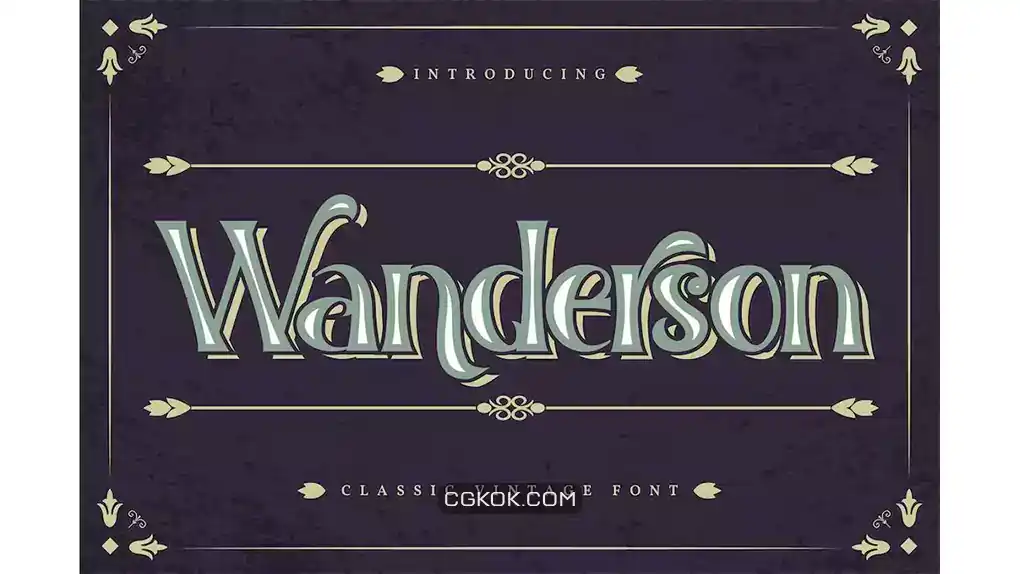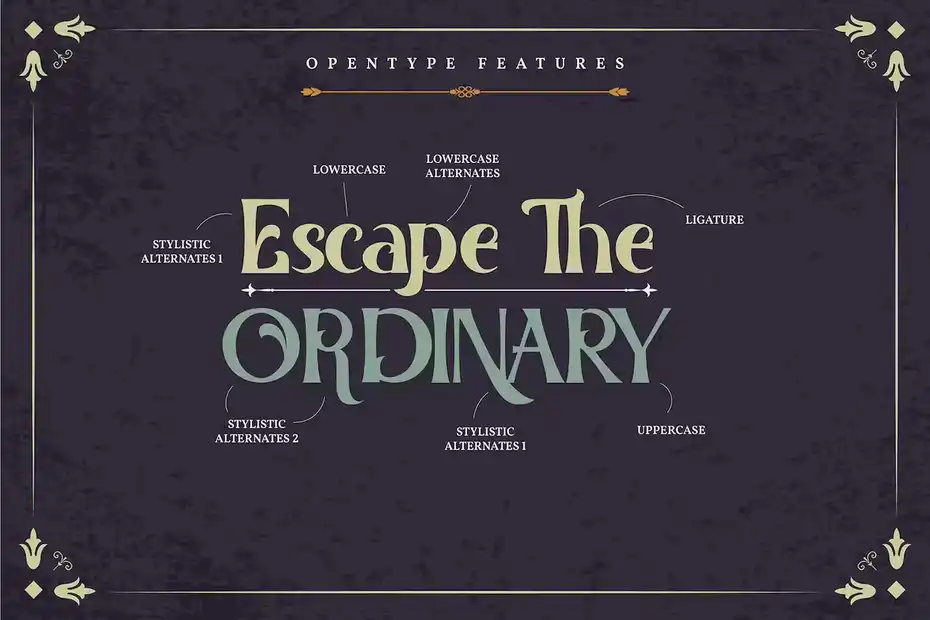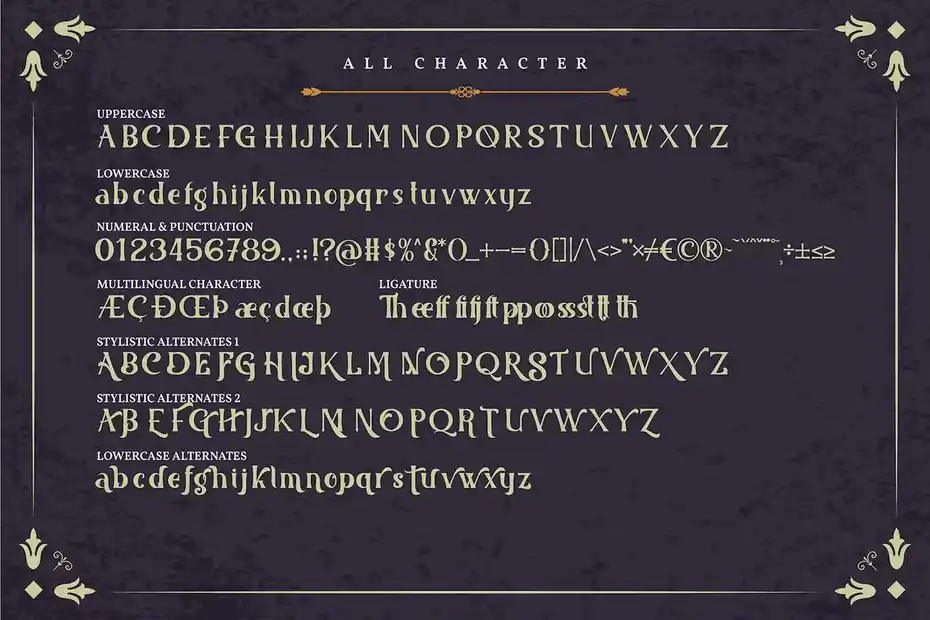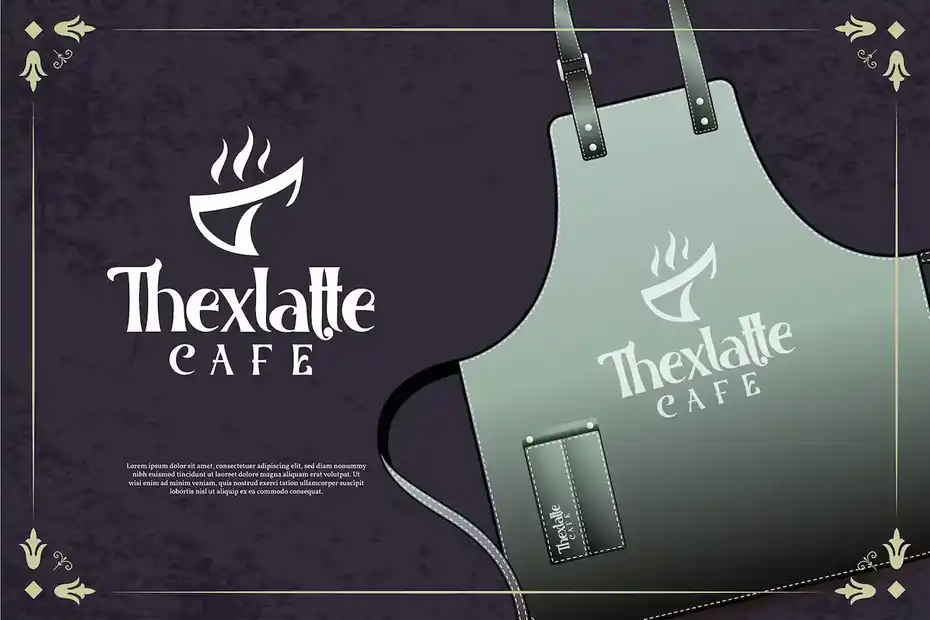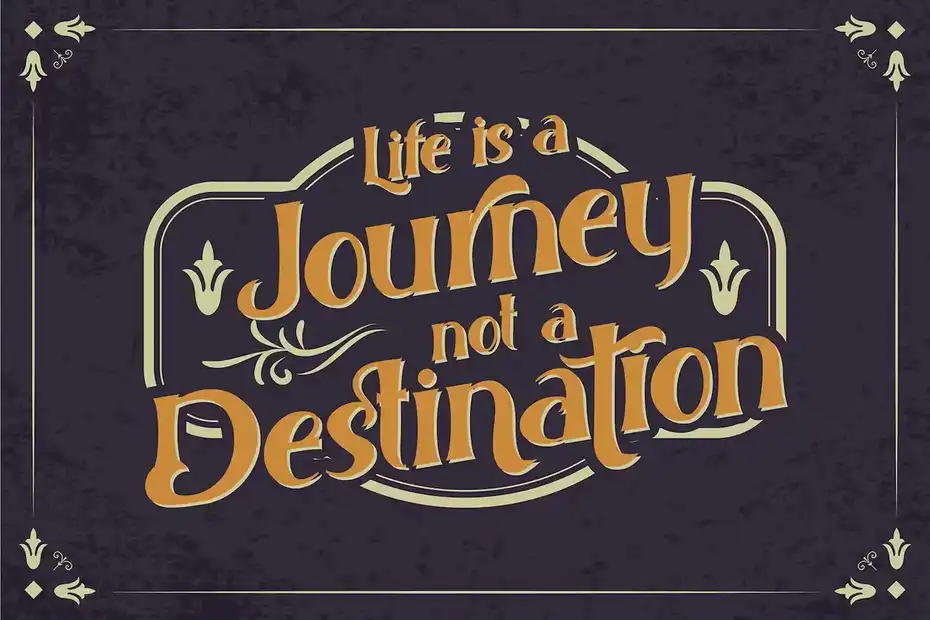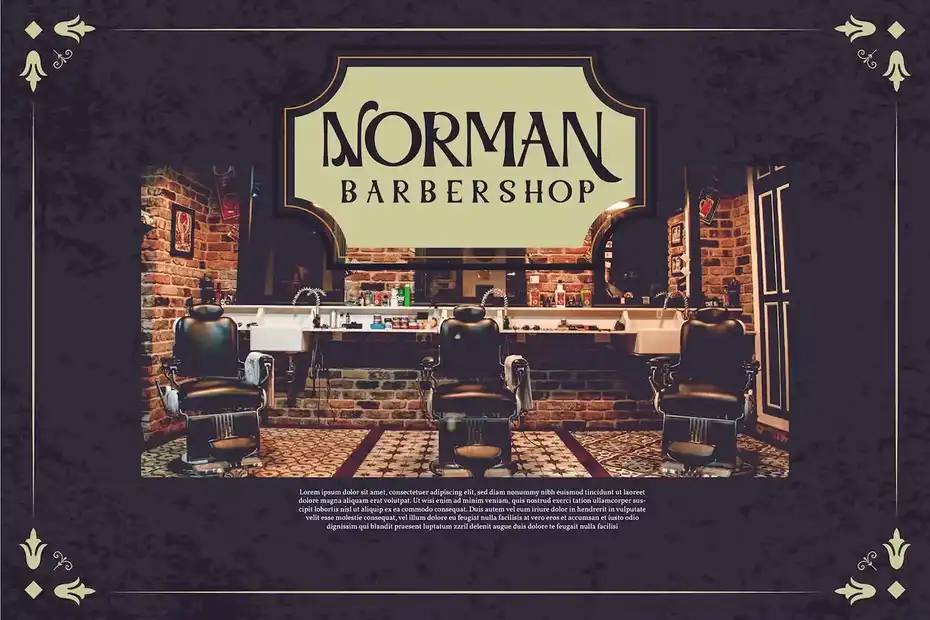
فونت انگلیسی کلاسیک Wanderson | Classic Vintage Font : این مجموعه شامل یک فونت انگلیسی کلاسیک است که برای برندینگ، کارت تبریک، کارت ویزیت، نقل قول، پوستر و غیره مناسب میباشد.
• فضا بین حروف: معمولی، متراکم، با فاصله
یه فونت با اصالت و زیبا.